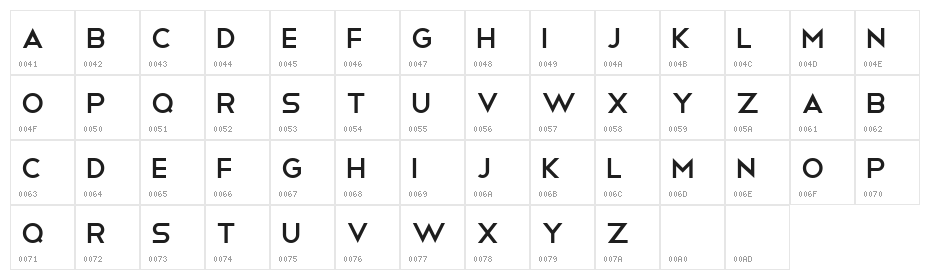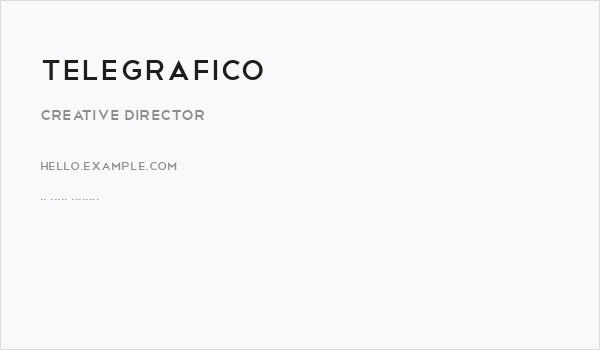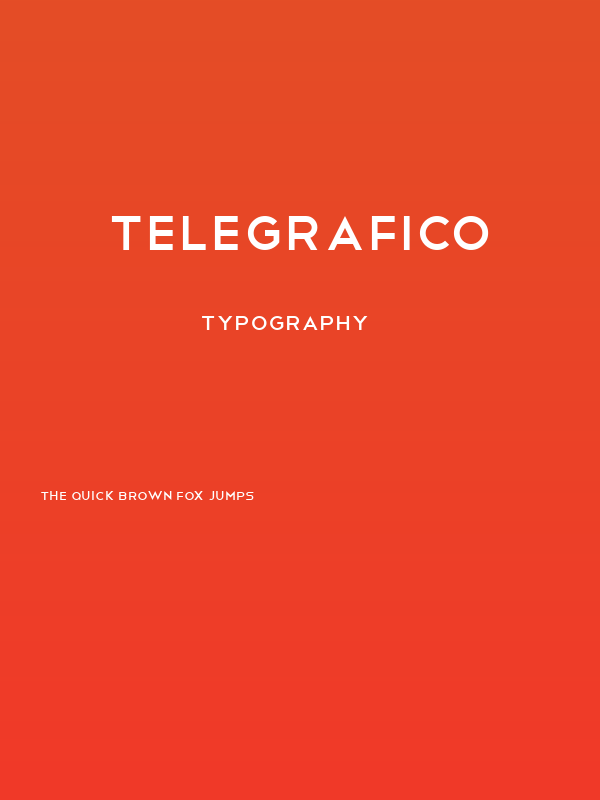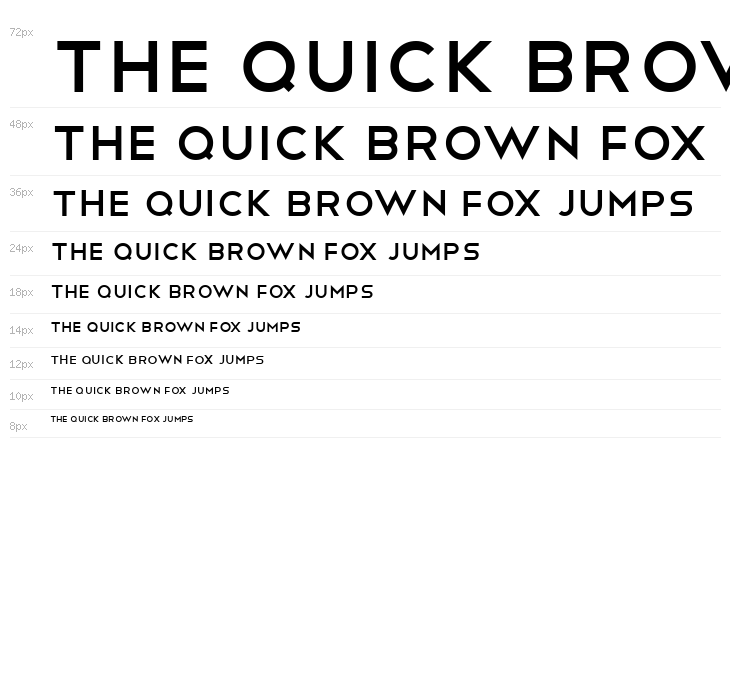
Telegrafico Font
✎ Sans Serif
| Категория | Sans Serif |
| Область применения | Coding, Technical documentation, Digital interfaces |
| Рекомендуемые проекты | Ideal for coding environments, technical documentation, digital interfaces, and minimalist branding projects. |